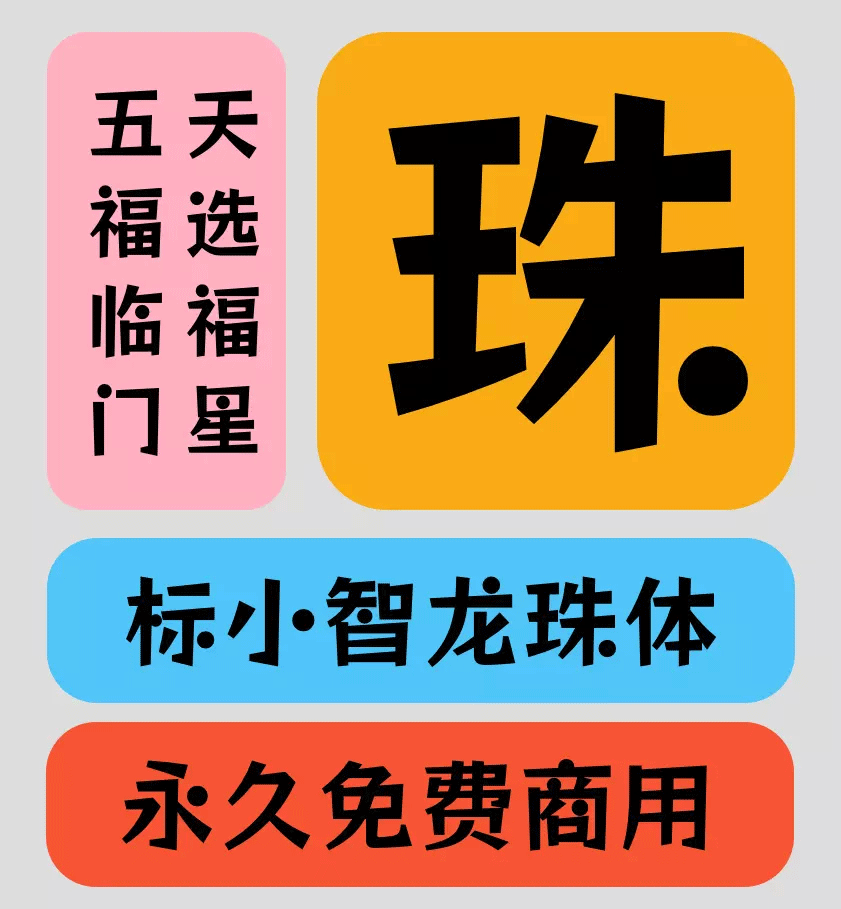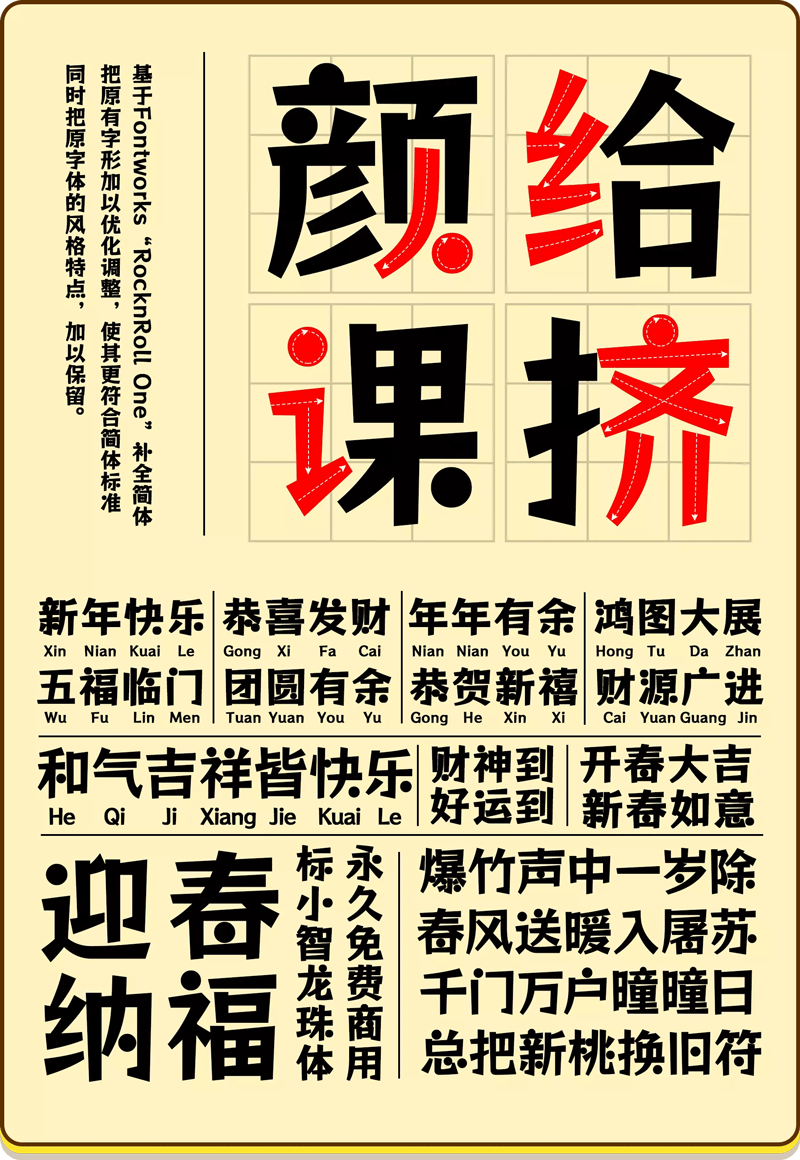
标小智龙珠体是标小智与猫啃网继标小智无界黑之后推出的第二款免费商用字体,它是基于日本著名字体设计公司 Fontworks 免费开源的”摇滚乐 One”(日文名:ロックンロール)字体进行简体字补充而开发的。
字体笔画粗壮有力,结构方正饱满,兼具力量感与卡通感。尤其是以实心圆点(龙珠)替代部分笔画,如点、撇、捺等,为字体营造了一种活泼、趣味的视觉效果。特别适合用于卡通类 LOGO 设计、儿童主题设计、母婴产品、萌系动画等场合,也可用于标题文字、海报字效、横幅标语等。